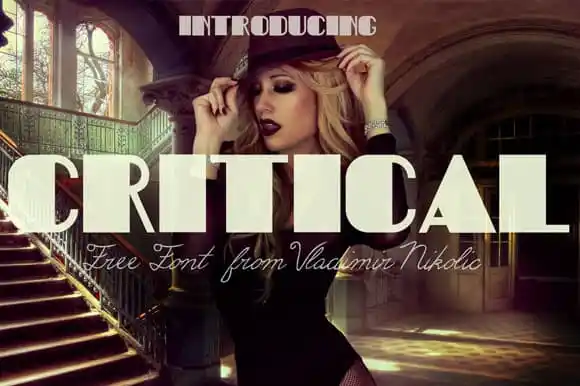
Critical Typeface – Fonte Grátis
Critical Typeface
Olá. Uma opção fantástica para adicionar algum charme à próxima sua criação visual é introduzir a Critical Typeface. Esta elegante fonte casual vem perfeitamente projetada para diversos tipos de projetos, como cartões de aniversário ou convites de casamento, decorações e logomarcas, entre outros interessantes trabalhos que exijam uma pitada de destaque no meio do design gráfico. Especialmente adequado para identificar um projeto único ou destacar certa mensagem, a Critical Typeface foi criada por Vladimir Nikolic e compartilhada gratuitamente pela Creative Fabrica. Se você está à procura de uma fonte para suas próximas criações de designs em sans serif, esta poderia ser uma ótima escolha.